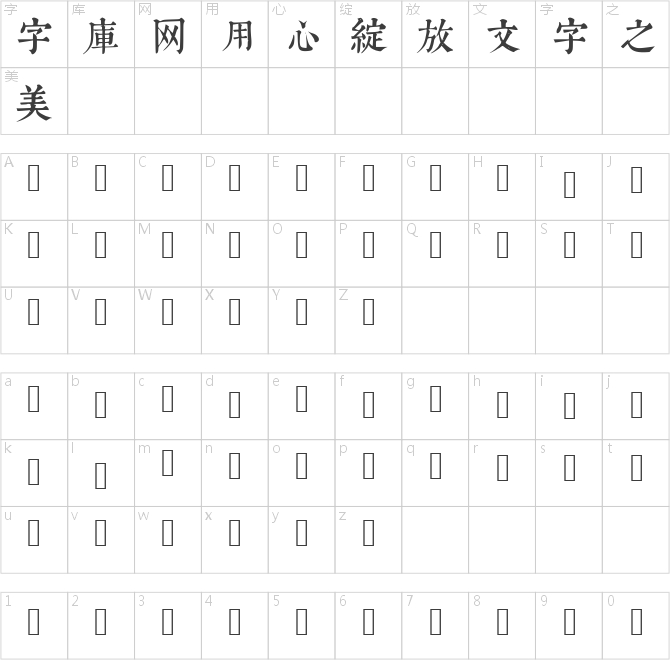
字體名稱: 康熙字典體常用
康熙字典體常用版
收字7000 個
我們推出的字體版本是電腦從七千多頁的《康熙字典武英殿版本》自動化切割字頭制作而成的。
我們仔細的計算了康熙字頭字收,總收字是47403個,雖借用電腦的自動切割可省下好多時間,但也要人工手動去翻七千多頁的《康熙字典武英殿版本》作字頭與古文篩選及刪掉多馀的字頭圖片,流程大致如下:
1)系統自動OCR版面切割并取出每一頁面的字頭圖片
2)手動把多馀的字頭圖片刪掉
3)手動定義古文字頭
4)系統自動排序字頭圖片
5)加入字序/Unicode
6)完成后即可點按字頭圖片取得文本內容及制作康熙字體等古籍數字化工作
關于收字范圍,常用版收字有約9000字,扣除因簡轉繁的重復字后有約7000個康熙字,收字主要參考《規范漢字表》及《繁體常用字表》,同時收字是在CJK基本漢字集內。
通用版收字約19000字,扣除因簡轉繁的重復字后有約17000個康熙字,主要在常用版收字之外再參考《繁體字次常用字表》及CJK基本漢字集內的康熙字。
完整版收字約49000字,扣除因簡轉繁的重復字后是47043個康熙字,也就是康熙字頭的完整收字。其實康熙字頭也有約80多個重復字,康熙字體采用Unicode 15 字集,沒有使用造字??滴踝值涫兆趾蚒nicode 的編碼是有少許不同之處及爭議的,尤其在Unicode 收字原則、異體字等方面,無論如何目前康熙字典采用Unicode做編碼及數字化仍是最佳的選
康熙字典體常用版字體字庫是一款讓人賞心悅目、百看不厭的中文字體,適合各類廣告和產品包裝設計應用,字體大小7.87MB,格式為ttf字體,上傳用戶是西西里,作者/版權方為康熙與倉頡